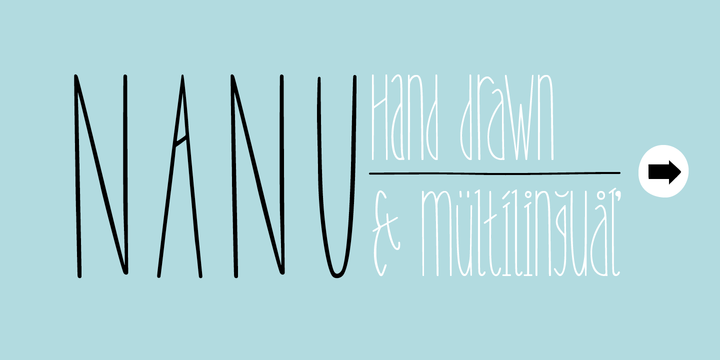
A Nanu é uma fonte desenhada à mão onde as letras maiúsculas e minúsculas têm a mesma altura do ápice, garantindo um equilíbrio visual que mantém a estética uniforme independentemente do tamanho da letra ou da tipografia usada. Esta fonte multilingue conta com uma vasta gama de recursos abertos, o que torna-a perfeita para projetos variados, desde designs gráficos até letras para websites e publicações. Ideal tanto para designers profissionais quanto para entusiastas do design, a Nanu oferece um equilíbrio entre estilo único e facilidade de uso. Ela não só adiciona um toque autêntico e pessoal aos projetos onde for aplicada, mas também inclui gratuitamente o conjunto de ornamentação simples da Nanu. Em sua descrição original em inglês, a fonte é referenciada como uma opção perfeita para quem busca uma mistura suave entre personalidade e flexibilidade, ideal tanto para criações digitais quanto impressas. Com a Nanu, você encontra uma escolha de qualidade que vai além da mera estética, oferecendo um conjunto de recursos abertos que aumentam ainda mais seu valor como fonte única.